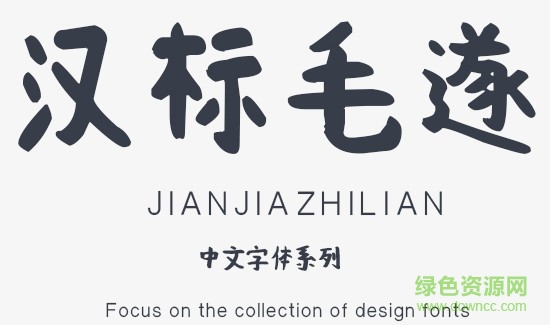
漢標(biāo)毛遂體是一款深受廣大用戶喜愛的毛筆書法字體,這款字體筆鋒粗曠,字形端正大方、線條簡潔利落,整體效果非常的出色,喜歡這款字體的朋友歡迎來綠色資源網(wǎng)免費(fèi)下載使用!
漢標(biāo)毛遂體超越了傳統(tǒng)思維模式,創(chuàng)造出新的書法藝術(shù)風(fēng)格,賦予書法特別的審美情趣,以其秀勁、爽利、古雅、飄逸之美獨(dú)領(lǐng)風(fēng)騷。漢標(biāo)毛遂體用筆一反秦漢以來幾千年的用筆規(guī)則,用筆直率簡練,舒展挺拔,秀美爽利,與傳統(tǒng)的楷書和隸書的用筆有明顯的不同。可謂直逼秦漢另出一體,為五體之外的第六書體。其秀勁爽利飄逸的字體,創(chuàng)建了隸書秀勁派的書風(fēng)。